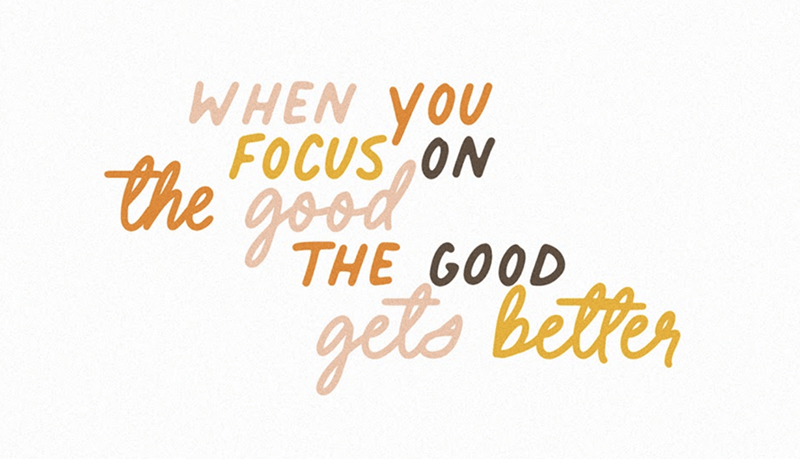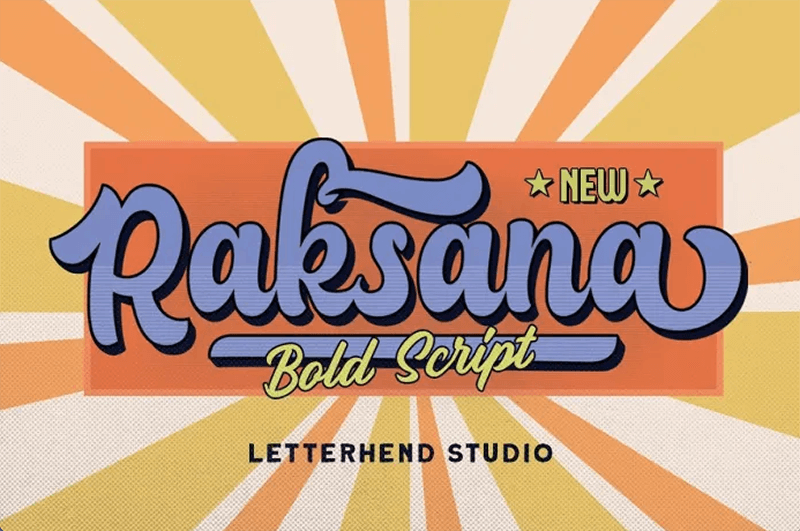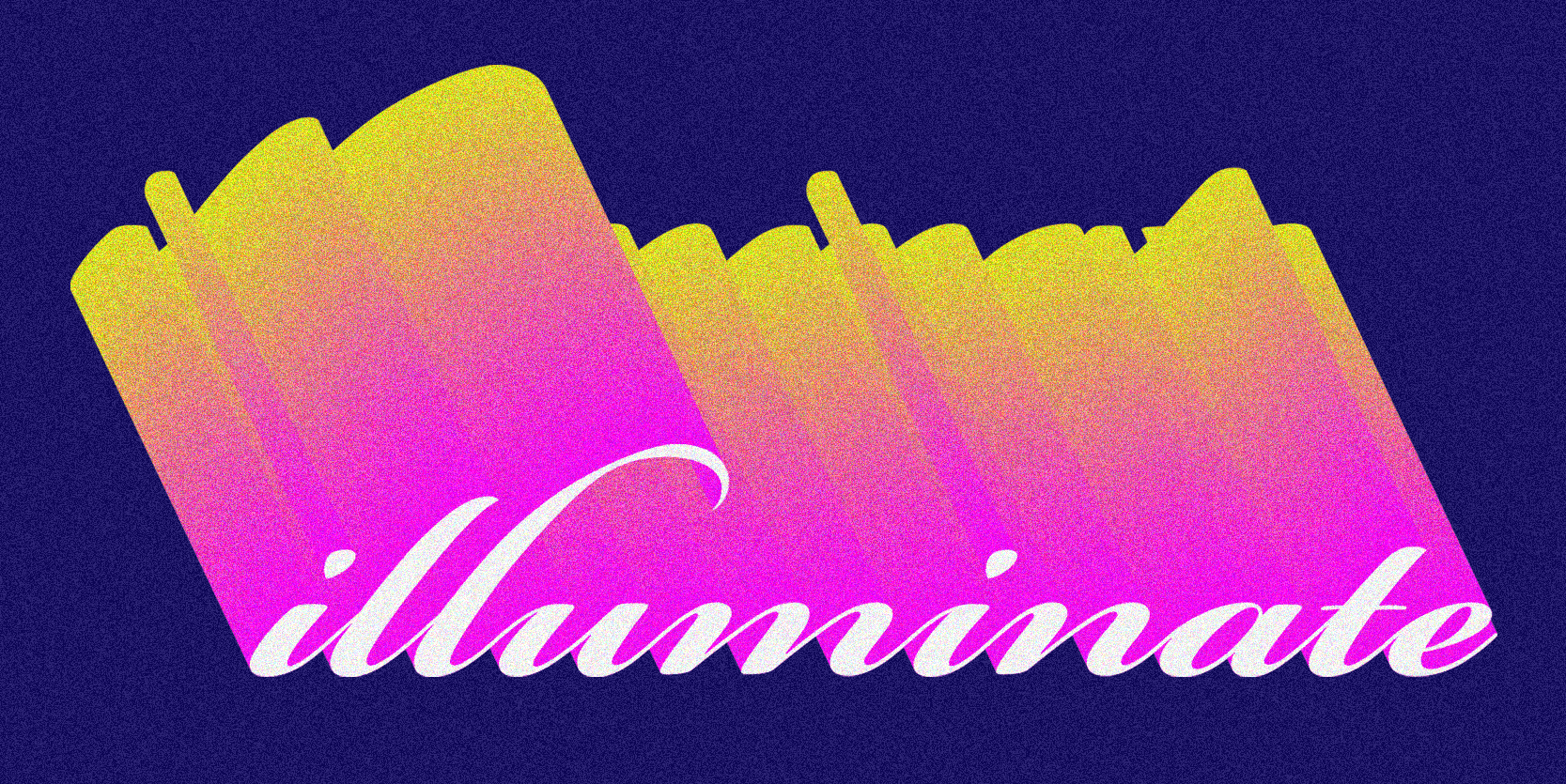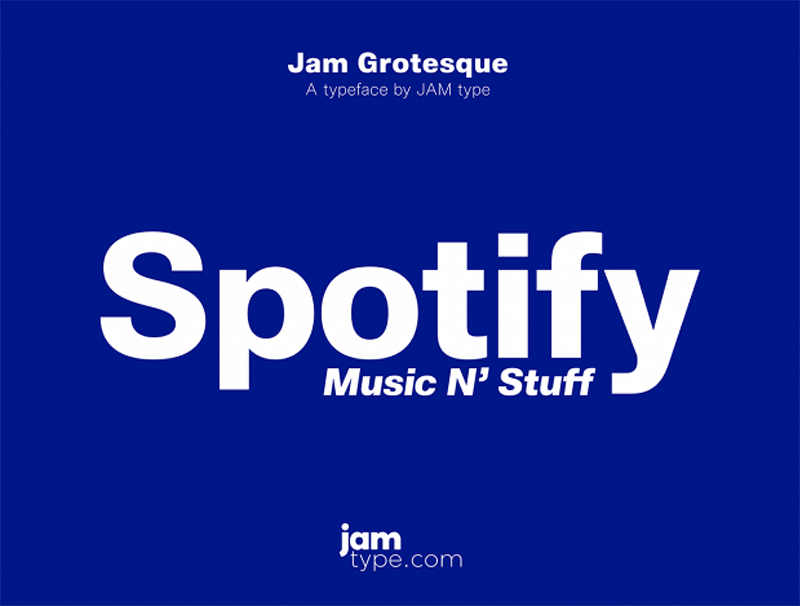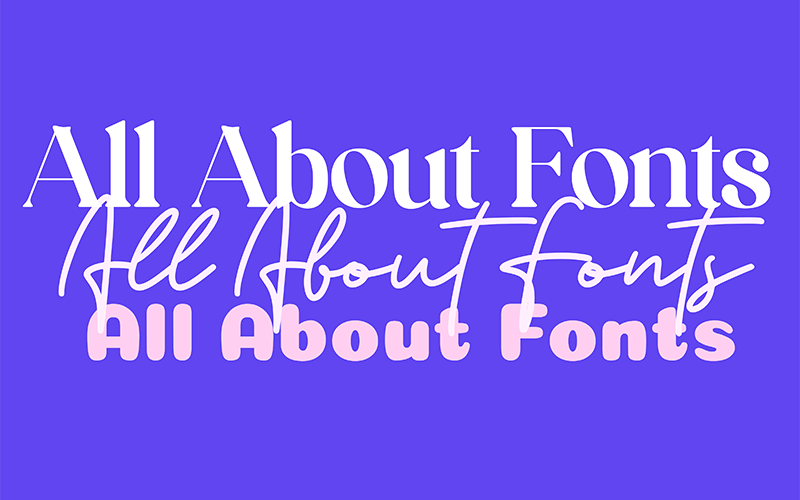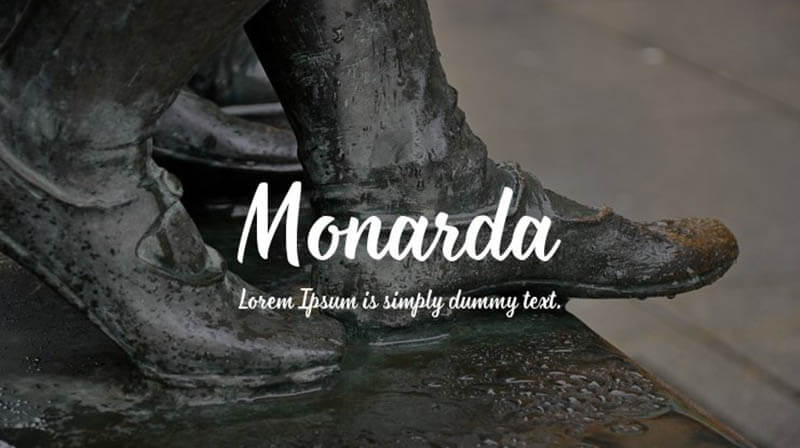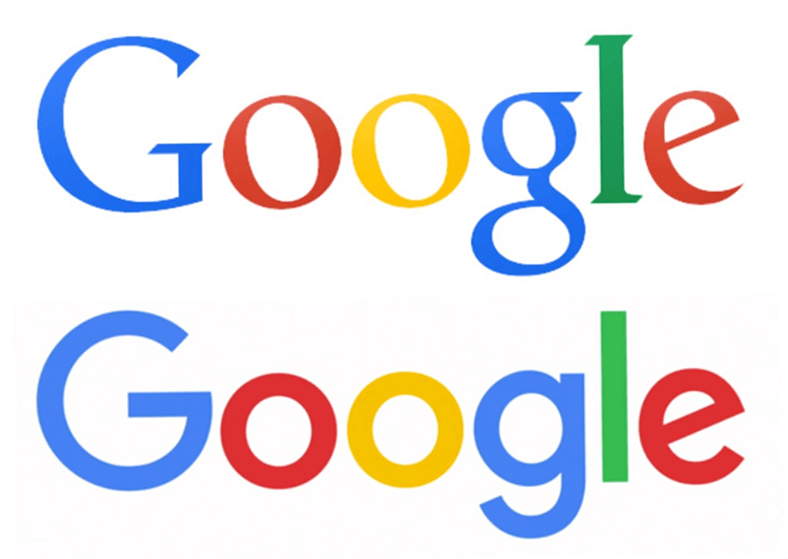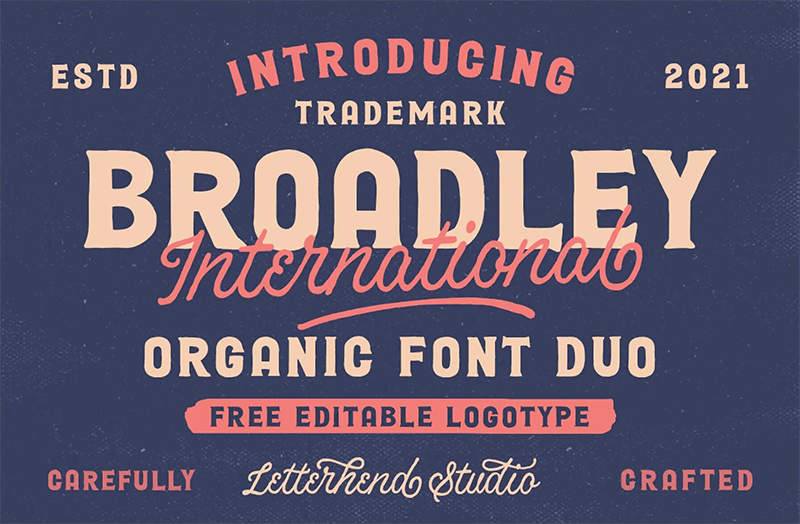
Tasarımınız İçin En İyi Yazı Tipi Logoları Nasıl Seçilir
Logo tasarımı her marka sahibi için çılgın bir maceradır, bu yüzden doğru yazı tipini seçmenin oldukça önemli olduğunu söylediğimizde bize güvenin! Sadece logonuzda değil, yazı tipinizi seçmek markalaşma sürecinizde büyük rol oynar. Yazı tiplerini küçümsemeyin! O halde daha fazla söze gerek yok ve yazı tipi logoları hakkında bilmeniz gereken her şeye dalın.
Logolar için en iyi yazı tipini seçmek için hedef kitlenizi, markanızın stilini ve logo tasarımınıza ne zaman ve nerede bakacaklarını göz önünde bulundurmalısınız. Hemen içine dalalım!
İdeal Yazı Tipinizi Nasıl Seçersiniz?
Daha önce de belirtildiği gibi, size doğru hisleri verdiği için bir yazı tipi seçmeden önce göz önünde bulundurmanız gereken birkaç şey var. Birkaç tanesinin üzerinden geçelim:
- Bir logo için en iyi yazı tipi, büyük veya küçük tüm boyutlarda okunaklı olandır.
- Logonuzun rakibinizle aynı görünmesini istemediğiniz için bir rakip araştırması yapın.
- Markanızın kimliğini yansıtın, tarzınızı yansıtan bir şey.
- Logonuzda birden fazla yazı tipi kullanmaktan kaçının, olabildiğince basit tutun.
- Modaya uygun yazı tiplerini kullanmaktan kaçının. Bugün popüler olan yarın olmayabilir. Moda trendlerine göre bir yazı tipi seçmeyin.
Logolar için En İyi Yazı Tipi Hangisi?
Aralarından seçim yapabileceğiniz tonlarca farklı yazı tipi vardır: serif, sans serif, el yazısı, el yazısı ve daha fazlası. Karar vermenize yardımcı olması için bunların her birine bir göz atalım.
Sans Serif Yazı Tipi Nedir?
Serif, bir harf satırının sonundaki kısa çizgidir. Bir sans (fransızca olmadan) serif yazı tipi, Time New Roman'ın yaptığı gibi uçlarında o küçük tire olmayan herhangi bir yazı tipi veya temelde tüm serif yazı tipleridir.
Sans serif yazı tipleri, modern logo yazı tiplerinin modern tipografileri olarak da bilinir . En bilinen sans serif yazı tipleri Arial, Helvetica, Proxima Nova, Futura, Calibri, Helvetica Now, Proxima Nova, Franklin Gothic, Myriad, ItalicTT Norms Pro ve Avenir Next ve diğerleridir.
En İyi Sans Serif Yazı Tipleri
Sans serif yazı tipleri , marka tasarımlarında kullanılacak en yaygın ve çok yönlü yazı tipleridir. Bunlar açık, okunaklı ve basittir. Çok yönlü oldukları için her türlü endüstri için inanılmaz derecede iyi çalışırlar. Genç ve erişilebilir bir görüntü istiyorsanız, bu tür yazı tipi kesinlikle gidilecek yoldur. Logonuzun daha ulaşılabilir ve eğlenceli görünmesini sağlamayı başaracaksınız!
Logo tasarımlarınızda kullanabileceğiniz en iyi Sans Serif yazı tiplerinden bazıları şunlardır:
Şimdi Helvetica
Proksima Nova
fütüra
Reçel grotesk
Geonik Pro
Ve diğerleri gibi: BR Cobane, Open Sans, Qualy, Vilane, Code Next Monaco, Spacia, Bequest, listenin büyük olduğu fikrini alırsınız.
En İyi Serif Yazı Tipleri
Daha klasik bir yol istiyorsanız, Serif yazı tipleri kesinlikle gitmeniz gereken yol. Serif yazı tipleri resmi ve sofistike görünür. Hukuk firmaları, finans firmaları ve daha fazlası gibi geleneksel endüstriler için mükemmel bir seçimdir.
En popüler Serif yazı tiplerinden bazıları , diğerleri arasında Times New Roman, Trajan, Baskerville ve Georgia Italic'tir .
En İyi El Yazısı Yazı Tipleri
Bitişik el yazısı, yüzyıllardır var olduğu için logonuz için daha klasik bir stildir. Bunlar güzel ve bakmak hoş, neredeyse elle çizilmiş. Logonuza insani bir dokunuş katmanın ince bir yolu.
El yazısı yazı tiplerinin uzun kelimelerde veya küçük ölçeklerde kullanıldığında tehlikeli olabileceğini ve okunmasının zor olabileceğini unutmayın.
Bu yıl logolar için en popüler el yazısı yazı tiplerinden birkaçı:
Broadley
Monarda
Palmer Gölü
raksana
Yağlı süt
Ve diğerleri gibi: Hope Sans, Elle yazılmış bitişik el yazısı yazı tipleri, Krysttal Spears, Estetik Notlar, Tahu, Billie Sights, Bilanthy, Diary Angelique, Stampa ve çok daha fazlası. Flanella, Debby, Variane, Beattingvile, Puzzled, Milkshake, Vegan Style ve daha fazlası gibi en iyi ücretsiz el yazısı yazı tiplerinden bazılarını bile kullanabilirsiniz .
En İyi Senaryo Yazı Tipleri
Komut dosyası yazı tiplerinin tümü, zarafeti, yaratıcılığı ve bir tutam insan dokunuşunu yansıtan bir kalemle yazılmış gibi, elle yazılmış bir stile sahiptir. Doğal el yazısını yansıtmak için tasarlanmıştır.
Şimdi düşünebilirsiniz, bu el yazısı yazı tipleriyle aynı değil mi? Cevap hayır. Komut dosyası yazı tipleri ile bitişik el yazısı arasındaki temel fark, komut dosyası harflerinin hepsinin birbirine bağlı olması, bitişik el yazısı yazı tiplerinin ise mutlaka olması gerekmemesidir.
Logonuz için mükemmel yazı tipini seçmek için her zaman hedef kitlenizin kim olduğunu, rakiplerinizin neye benzediğini ve insanların logonuza ne zaman ve nerede bakacağını düşünün!